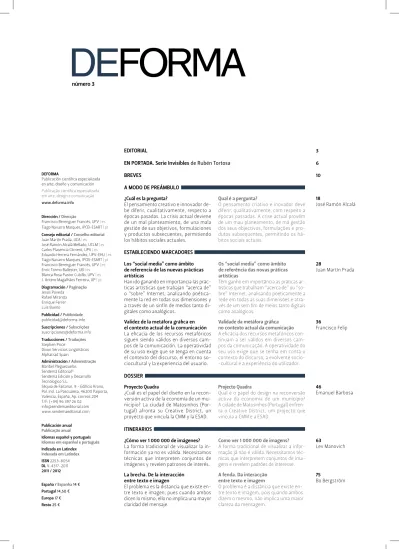
Comisarios de diseño ante la necesidad de un código deontológico La figura del comisario en el área del di-seño es relativamente reciente y provie-ne del mundo del arte. Una especialidad que surgió ante la necesidad de los mu-seos de organizar exposiciones de diseño, marcando un paralelismo con las funcio-nes propias del comisario de arte. MEDIOS
Comissários de design perante a necessidade de um código deontológico A figura do comissário na área do de-sign é relativamente recente e provém do mundo da arte. Uma especialidade que surgiu perante a necessidade dos museus em organizar exposições de de-sign, marcando um paralelismo com as funções próprias do comissário de arte.
El problema es la solución. La eterna muerte y resurrección de la pintura como disciplina artística En el arte actual la ironía ha sufrido una evolución hacia el cinismo, permitiendo que la exageración y el escándalo deri-ven de su mutación a la que se le ha ex-traído su antiguo sentido ético y moral. De este modo, hablamos de la ironía y el cinismo en la pintura del siglo XXI.
O problema é a solução. A eterna morte e ressureição da pintura como disciplina artística Na arte actual a ironia sofreu uma evo-lução para o cinismo, permitindo que o exagero e o escândalo derivem da sua mutação, à qual se extraiu o seu antigo sentido ético e moral. Deste modo, fala-mos da ironia e do cinismo na pintura do século XXI.
Del paradigma del ver al de tocar: El devenir háptico en la creación artística contemporánea
¿Cuál es el papel de la percepción háptica ante la intensificación de los estímulos sensoriales de la cultura digital? La per-cepción háptica reclama un lugar central en la experiencia interactiva, en tanto el arte interactivo es, por definición, esen-cialmente táctil.
Do paradigma do olhar ao do tocar: O devir háptico na criação artística contemporânea
Qual o papel da percepção háptica pe-rante a intensificação dos estímulos sensoriais da cultura digital? A percep- ção háptica reclama um lugar central na experiência interactiva, visto a arte in-teractiva ser, por definição, essencial-mente táctil.
Espacio verbal vs no-verbal, el problema de la tipografía
Podemos definir la tipografía como forma de procesar el espacio visual del lenguaje verbal, que incluye no sólo la forma de la letra, sino también el contra-grafismo, espacio en blanco o no-verbal.
Espaço verbal vs não-verbal,
o problema da tipografia
Podemos retratar a tipografia como a for-ma de processar o espaço visual da lingua-gem verbal, incluindo não apenas a forma da letra, mas também o contra-grafismo, espaço em branco ou não-verbal.
98 Marcelo Leslabay 116 Antonio García 126 Salif Silva 110 Tiago Navarro Marques
Todos los derechos reservados. En virtud de lo dispuesto en los artículos 8 y 32.1, párrafo segundo de la Ley de Propiedad Intelectual, quedan expresamente prohibidas la reproducción, la distribución y la comunicación pública, incluida su modalidad de puesta a disposición, de la totalidad o parte de los contenidos de esta publicación, con fines comerciales en cualquier soporte y por cualquier medio técnico, sin la autorización de la editorial. Todos os direitos reservados. Em virtude do disposto nos artigos 8 e 32.1, segundo parágrafo da Lei de Propriedade Intelectual, ficam expressamente proibidas a sua reprodução, distribuição e a comunicação pública, incluída o seu modo de colocação à disposição, da totalidade ou parte dos conteúdos desta publicação, com fins comerciais em qualquer suporte e por qualquer meio técnico, sem a autorização da editora. BIBLIOTECA SUSCRIPCIÓN ENVÍO DE ORIGINALES 86 Francisco Berenguer
DIÁLOGO CON VICENTE GUALLART Internet ha posibilitado un uso singular del espacio, extraordinariamente sen-sible a los acontecimientos virtuales y su consumo; abierto a la interacción del usuario. Al respecto, lo urbano deman-da una reconsideración de sus procesos de configuración y transformación.
Internet possibilitou um uso singular do espaço, extraordinariamente sensível aos acontecimentos virtuais e seu con-sumo; aberto à interacção do utilizador. A este respeito, o urbano contesta uma reconsideração dos seus processos de configuração e transformação.
135 141 143
Con este número tres, la revista GRAFEMA cambia su denomina-ción por DEFORMA y amplía su cobertura temática al ámbito del arte, el diseño y la comunicación, con contenidos amplios, profun-dos y concluyentes. De naturaleza científica y revisada por pares, DEFORMA publica artículos en dos idiomas, español y portugués, procurando una causa que merezca la generosidad de aquellos lectores que demandan precisión y rigor en la información, sin voluntad de eliminar, por ello, el componente divulgativo de sus contenidos. Una publicación con pasado y avatar, que pretende establecerse como aquel lugar donde se trata de la cultura, enten-diendo como lugar un conjunto de reflexiones circunscritas a una concurrencia de cualificados especialistas.
A este número tres de la revista le corresponde, también, evaluar la situación de nuestra realidad cultural, de su técnica, de su pro-ducción, de su comunicación, de su difusión, de su circulación, ante una sociedad con dificultades por las crisis que le afectan. Es evidente que una producción social es la condición de una producción cultural, implica dependencia y relaciones de fuerza; inherentes entre sí, la primera se encierra en el círculo de la se-gunda. La acción urgente consiste en intervenir allí donde ellas se articulan, pues no se puede disociar aquí el acto de comprender el entorno de la voluntad de cambiarlo. Es necesario buscar los es-tratos en función de los cuales se desarrolla nuestra realidad cul-tural e identificar y delimitar cuáles son sus problemas actuales. Ahora bien, no estamos hablando de problemas de acción, sino de conocimiento, es decir, hechos y procesos conectados a las nece-sidades propias de nuestro campo de estudio. En tal caso, no hay respuesta definitiva a nuestro interrogante. En ¿cuál es el proble-ma? la infinitud alcanza tanto al enunciado como a la enunciación. La misma pregunta se antoja indefinida pues los problemas por resolver implican la necesidad de hallar la respuesta a una cues-tión indagada, lo cual nos lleva, irremediablemente, a establecer más preguntas pero, ¿cuáles son estas preguntas? En este proceso creativo del pensamiento, su formulación correcta nos posibilita-rá abrir áreas de genuina construcción conceptual, dando lugar a convenientes respuestas.
Probablemente, cualquiera que sea la amplitud de la documen-tación recopilada en este número, el riguroso intento por fijar las ideas, o las aportaciones surgidas en torno al tema específico de la revista, concretan un cúmulo de reflexiones que, lejos de quedar atrapados por los bordes del tiempo, tienen la necesidad de prose-guir en la búsqueda de respuestas.
Francisco Berenguer
Com este número três, a revista GRAFEMA muda a sua denomi-nação para DEFORMA e alarga o seu horizonte temático ao âmbito da arte, do design e da comunicação, com conteúdos vastos, pro-fundos e conclusivos. De natureza científica e revisada por pares, DEFORMA publica artigos em dois idiomas, espanhol e português, procurando uma causa que mereça a generosidade de aqueles lei-tores que procuram precisão e rigor na informação, sem descartar, por isso, a componente de divulgação dos seus conteúdos. Uma publicação com passado e avatar, que pretende estabelecer-se como aquele lugar onde se trata da cultura, definindo-se como lu-gar aquele conjunto de reflexões circunscritas a um fluxo de qua-lificados especialistas.
A esta edição número três da revista corresponde-lhe, também, avaliar a situação da nossa realidade cultural, da sua técnica, pro-dução, comunicação, difusão, circulação, perante uma sociedade com dificuldades pela crise que a afecta.
É evidente que uma produção social é a condição de uma pro-dução cultural, implica dependência e relações de força; ineren-tes entre si, a primeira encerra-se no círculo da segunda. A acção urgente consiste em intervir onde elas se articulam, pois não se pode dissociar aqui o acto de compreender o ambiente da von-tade de muda-lo. É necessário procurar os estratos em função dos quais se desenvolve a nossa realidade cultural e identificar e delimitar quais são os seus problemas actuais. Mas não estamos a falar de problemas de acção, mas sim de conhecimento, quer dizer, factos e processos conectados às necessidades próprias do nosso campo de estudo. Neste caso, não existe resposta de-finitiva à nossa interrogação. No “qual é o problema?” o infinito alcança tanto o declarado como a proposição. A mesma pergun-ta parece indefinida como os problemas por resolver implicam a necessidade de encontrar a resposta a uma questão indagada, o qual nos remete, inevitavelmente, a estabelecer mais perguntas mas, quais são estas perguntas? Neste processo criativo do pen-samento, a sua formulação correcta possibilita-nos abrir áreas de genuína construção conceptual, administrando lugar a conve-nientes respostas.
Provavelmente, qualquer que seja a amplitude da documentação recompilada neste número, a rigorosa tentativa por fixar as ideias, ou as contribuições surgidas em volta do tema específico da re-vista, materializam num acumular de reflexões que, longe de ficar apanhados pela borda do tempo, têm a necessidade de prosseguir na procura de respostas.
110 | DEFORMA | 111
La tipografía se establece en la página como el verdadero problema para el usuario, pero no como el eterno miedo de los escritores al espacio en blanco. Muy al contrario, este es-pacio proporciona el oxígeno que la tipografía necesita para sobrevivir, ya que se trata de la burbuja de aire que la fuente necesita para su normal funcionamiento. Este factor que es bá-sicamente técnico, la mayoría de las veces no se consigue alcanzar utilizando solo la técnica. La célebre frase Less is more, acuñada por el famoso arquitecto Mies van de Rohe y apli-cada en sus proyectos, tan entendida entre la comunidad de diseñadores, es la adjetivación perfecta en la relación entre el tipo y la matriz. Es bien sabido que si proyectamos tipos para espacios con distintas dimensiones, no
pode-mos utilizar fuentes idénticas —por no hablar de la propia dimensión— aunque en tal caso intervenga la subjetividad. Así como, también, que la complejidad de la construcción de un tipo puede interferir significativamente en su lectura, aunque aquí además pueda de- pender de su contexto, más aún si nos cen-tramos en el ámbito editorial, donde se revela como la más íntima y aquella que mejor pone en práctica los fundamentos de la tipografía. En definitiva, una letra con características gó- ticas no funciona para bloques de texto; al contrario, un carácter romano —mayor deta-lle formal que un carácter de palo seco— fun-ciona a la perfección para el mismo texto pues permite que el lector no pierda el hilo conduc-tor de la lectura.
PALABRAS CLAVE TIPOGRAFÍA, DISEÑO, MEDIOS DE COMUNICACIÓN, DSTYPE, DIGITAL
Espacio verbal vs no-verbal
TIAGO NAVARRO MARQUES
Instituto Politécnico de Castelo Branco, PortugalEL PROBLEMA DE LA TIPOGRAFÍA
PALAVRAS-CHAVE TIPOGRAFIA, DESIGN, MEDIA, DSTYPE, DIGITAL
Espaço verbal vs não-verbal
TIAGO NAVARRO MARQUES
Instituto Politécnico de Castelo Branco, PortugalO PROBLEMA DA TIPOGRAFIA
Si tenemos en cuenta la comunicación, ¿dónde reside el
verdadero problema de la tipografía, en el espacio verbal
o no-verbal? Muchas son las aplicaciones que intentan
desvelar cual tiene mayor peso, veamos aquí un ejemplo
práctico de la agencia portuguesa DSType
A tipografia por si só assume-se perante a página como o verdadeiro problema para o utilizador, mas não pelo eterno sindroma dos escritores — o espaço em branco. Bem pelo contrário, este espaço é o oxigénio que a tipo-grafia necessita para sobreviver, pois trata-se da bolha de ar que a fonte necessita para o seu funcionamento positivo. Falamos obviamente de usabilidade quando nos referimos a funcio-namento. Este factor é puramente técnico, que na maioria das vezes não se consegue atingir utilizando apenas a técnica.
A célebre frase Less is more, adaptada pelo fa-moso arquitecto Mies van der Rohe e aplicada nas suas obras, tão bem entendida entre a co-munidade de designers, é a adjectivação perfei-ta na relação entre o tipo e a matriz.
Evidente-mente que projectar para espaços de dimensões distintas não podemos utilizar fontes idênticas, já para não falar da própria dimensão, ainda que este patamar seja ostentado por subjectividade. Tal como a complexidade de construção de um tipo poder interferir significativamente na lei-turabilidade, embora aqui também dependa do seu contexto. Mais ainda se nos posicionarmos num contexto editorial, revelando-se como a mais íntima e aquela que melhor põe em prá-tica os fundamentos da tipografia. Definitiva-mente, uma letra com características góticas não funciona para texto corrido; por outro lado, um carácter romano — maior detalhe formal que um carácter sem patilha — funciona na per-feição para o mesmo texto já que permite com que o leitor não perca o fio condutor de leitura.
Tendo em conta a comunicação, onde será que reside
o verdadeiro problema da tipografia, no espaço verbal
ou não-verbal? Muitas são as aplicações que tentam
desvendar qual terá maior peso, vejamos aqui um
exemplo prático do atelier português DSType
112 | DEFORMA | 113 1. Consultor de arquitectura visual.
García, Mario: Contemporary Newspaper
Design: A Structural Approach. The
Poynter Institute for Media Studies. Prentice Hall, USA, 1993.
2. Bringhurst, Robert: The Elements
of Typographic Style. Hartley & Marks,
Publishers, Canadá, 2002. 3. Entrevista en el periódico La Voz
de Galicia a propósito de su trabajo
desarrollado [08-01-2011].
Volviendo a la cuestión inicial —la importan-cia del espacio en blanco en las fisuras de la tipografía— veamos un ejemplo actual, reali-zado por el diseñador de tipos Dino dos Santos (DSType) a propósito del rediseño del periódico La Voz de Galicia. Sin eliminar del todo el so-porte analógico, en la última década la prensa periódica ha asumido y adaptado sus medios de comunicación a un nuevo soporte que se reafirma, el digital, más aún con la introduc-ción de los tablets que en los últimos años han revolucionado definitivamente el merca-do. Los diseñadores de tipos se enfrentan con esta preocupación creciente, pues más allá del requisito indispensable de la legibilidad de una fuente, esta tiene que ser consumida. Su adaptación a estas nuevas plataformas reve-la un gran rigor analítico, capaz de entender, y fusionar, la letra en la matriz. Es lo que nos expresa el reciente trabajo de Dino dos Santos con el perfeccionamiento de la identidad del periódico de Galicia. Respetando su identidad, han sido retocados ciertos detalles formales —aumento de los espacios en blanco— al abrir y garantizar la comunicación. No hay duda que en el mercado de la prensa periódica son nece-sarios atributos de distinción, para marcarse o diferenciarse, y la fuente es un elemento que asume gran importancia al servir como
ima-gen e identificación de un producto. Al analizar la transición generada, confirmamos exacta-mente la preocupación de Santos para con el elemento Blanco. Este resalta como protago-nista figurante, asumiendo el papel principal parejo a la forma-letra.
Este trabajo realizado comparte la teoría de varios expertos como Mario García 1 o Robert Bringhurst 2, los cuales describen la fuente como uno de los elementos más importantes en el diseño de un periódico. Bringhurst va más allá, describe como estrategia para la elección del tipo, la lectura del texto. Interpretar para comunicar mejor. Conocer el contenido se vuelve esencial, como también fundamental tenerlo de aquellos que serán los descodifica-dores del mensaje. La estructura, dimensión física, área gráfica y el espacio que debe per-manecer en blanco, son algunas facultades de la forma tipográfica.
Para reafirmar la importancia en la elección de un tipo, y su distinción, Santos sostiene 3 que al igual que la tipografía también las personas son iguales en lo que concierne a elementos comu-nes: cara, ojos, orejas, nariz y boca. Sin em-bargo, nadie se confunde en el aprendizaje de nuestra propia experiencia, donde percibimos las pequeñas diferencias. El tipógrafo portu-gués asevera que lo mismo sucede con la
tipo-Voltando à questão inicial, a importância do branco nas fissuras da tipografia, vejamos um exemplo actual, executado pelo typefacer Dino dos Santos (DSType) a propósito do redesign do jornal La Voz de Galicia. Não eliminando de todo o suporte analógico, na última década a imprensa periódica tem assumido, e adapta-do, os seus meios de comunicação para um novo suporte que começa a afirmar-se, o di-gital. Mais ainda com a introdução dos tablets, que nos últimos anos têm agitado, definitiva-mente, o mercado. Os typefacers deparam-se agora com esta preocupação acrescida, para além de ser impreterível que uma fonte seja legível, esta terá que ser consumida. A sua adaptação para estas novas plataformas tem revelado um grande rigor analítico, capaz de entender, e conjugar, a letra na matriz. É o que revela o recente trabalho de Dino dos Santos com o retoque da identidade do periódico da Galiza. Respeitando a identidade do periódico, foram modificados certos detalhes — aumento do branco — de forma a abrir, e garantir a co-municação. Não existem dúvidas que no mer-cado da imprensa periódica são necessários atributos de distinção, marcar ou diferenciar, e a fonte é um elemento que assume grande im-portância e que serve de imagem e reconhe-cimento de um produto. Ao desvendar a
tran-sição efectuada, confirmamos exactamente a preocupação de Santos para com o elemento
Branco. Este passa de um mero personagem figurante, assumindo o papel principal a par da
forma–letra.
Este trabalho realizado reflecte-se na teoria de vários especialistas como Mario García 1 ou
Robert Bringhurst 2, em que referem a fonte
como um dos elementos mais importantes no
design de um jornal. Bringhurst vai mais longe,
descreve como táctica na escolha do tipo a lei-tura do texto. Decifrar para melhor comunicar. O conhecimento do conteúdo torna-se indis-pensável, como é fundamental ter conheci-mento daqueles que serão descodificadores da mensagem. A estrutura, dimensão física, man-cha gráfica e o espaço que deve permanecer em branco, são algumas faculdades da forma tipográfica.
Como reforço da importância na escolha de um tipo, e sua distinção, Santos refere 3 que a par
da tipografia, também as pessoas são todas iguais no que respeita a elementos comuns: cara, olhos, orelhas, nariz e boca. No entanto ninguém se confunde pela aprendizagem da própria vida, onde entendemos as pequenas diferenças. O tipógrafo portuense diz que o mesmo se passa na tipografia, mas que o pro-blema é que as pessoas não estão habituadas
Perspectiva del periódico La Voz de Galicia, 2011
Dino dos Santos
Perspectiva do jornal La Voz de Galicia, 2011
1. Consultor de arquitectura visual. García, Mario: Contemporary Newspaper
Design: A Structural Approach. The
Poynter Institute for Media Studies. Prentice Hall, USA, 1993.
2. Bringhurst, Robert: The Elements
of Typographic Style. Hartley & Marks,
Publishers, Canadá, 2002. 3. Entrevista ao jornal La Voz de
Galicia a propósito do seu trabalho ali
114 | DEFORMA | 115
grafía y el problema consiste en que las perso-nas no están acostumbradas a observarla sin detectar sus elementos diferenciadores al no formar parte de su sistema de reconocimiento. En suma, podemos describir la tipografía como la forma de procesar el espacio visual del len-guaje verbal, incluyendo no solo la forma de la letra, sino también el contra-grafismo, el espa-cio en blanco o no-verbal. Este es verdadera-mente uno de los principales problemas en la sistematización de una fuente, el pasaje del cur-sus al ductus de la letra, entendida como el tra-zo y el modo en que la herramienta recorre esa misma estructura, constituyendo así el cuerpo. La preocupación del diseñador de tipos es ele-
vada si tenemos en cuenta este campo, de enorme sensibilidad. En una gaveta tipográfica encontramos un ejemplo análogo perfecto de esta necesidad, pues sus divisorias necesitan un espacio lo suficientemente amplio para que puedan caber un conjunto de glifos comunes, así como el área del ojo de la letra que tendrá que estar libre para que esta se pueda visuali-zar. Aquí encontramos otros conceptos vincu-lados a la estructura de una letra y su relación familiar, como la arquitectura gráfica. Así, el blanco, aquel campo que supuestamente no es consumido, consigue tener el poder suficiente-mente elevado para una fuente sea eficaz, es decir, comunicable.
Infografía de los diferentes pesos de blanco existentes en el contra-grafismo de las letras L, G y a Infografia dos diferentes pesos de Branco existentes no contra-grafismo das letras L, G e a
a observá-la, sem detectar os seus elementos diferenciadores por não fazer parte do seu sis-tema de reconhecimento.
Em suma, podemos retratar a tipografia como a forma de processar o espaço visual da lingua-gem verbal, incluindo não apenas a forma da letra, mas também o contra-grafismo – espaço em branco ou não-verbal. Este é verdadeira-mente um dos principais problemas na siste-matização de uma fonte, a passagem do cursus para o ductus da letra, entendida como o traço e a forma como a ferramenta percorre nes-sa mesma estrutura, atribuindo-lhe o corpo. A preocupação do typefacer é elevada, tendo
em conta esta zona com que se depara, de enorme sensibilidade. Numa gaveta tipográfi-ca encontramos um exemplo análogo perfeito desta necessidade, pois as suas divisórias ne-cessitam do espaço o bastante amplo para que se possa encaixar um conjunto de glifos co-muns, bem como da área do olho da letra liberto para que esta se possa visualizar. Aqui encon-tramos outros conceitos aliados à estrutura de uma letra, e sua relação familiar, como a arqui-tectura gráfica. Assim, o branco, aquele campo que supostamente não é consumido, conse-gue ter o poder suficientemente elevado para que uma fonte seja eficaz, ou seja, comunique.
Transición entre el cursus (abajo) y el ductus (en el centro) de Galicia Transição entre o cursus (em baixo) e o ductus (centro) de Galicia